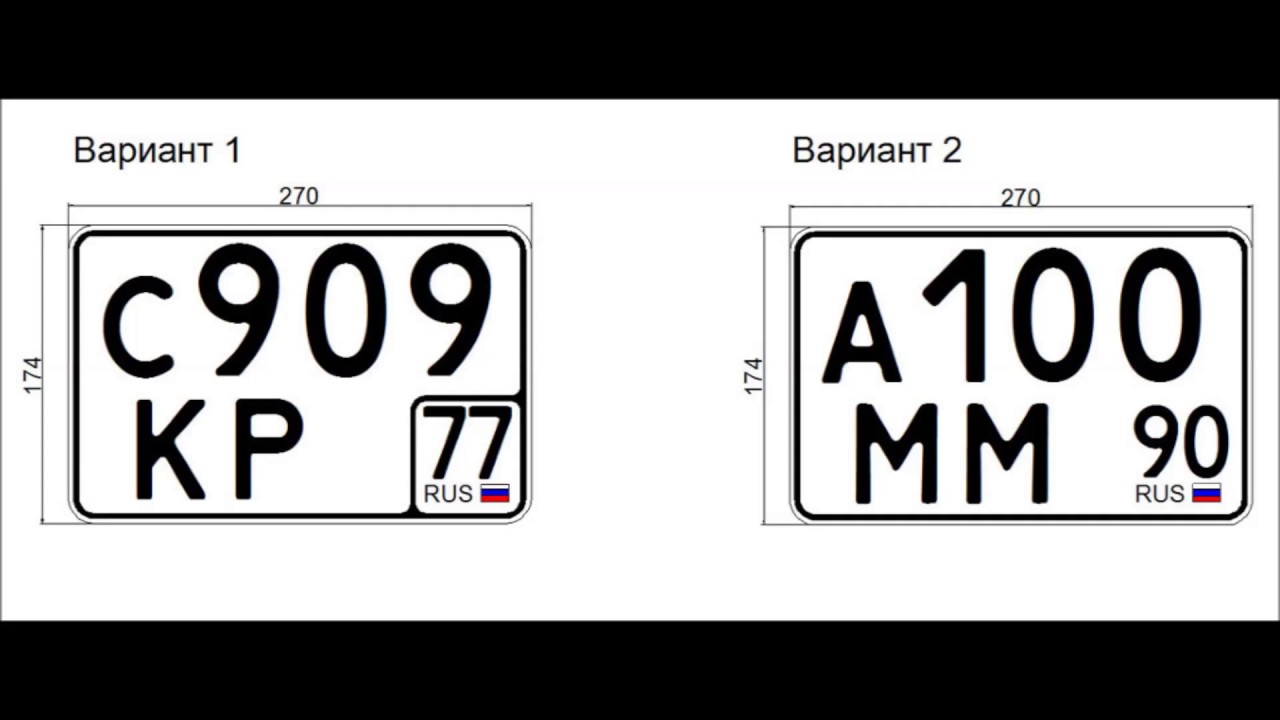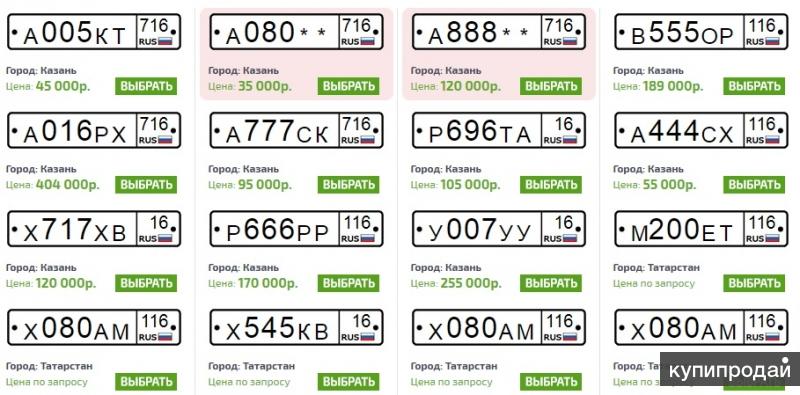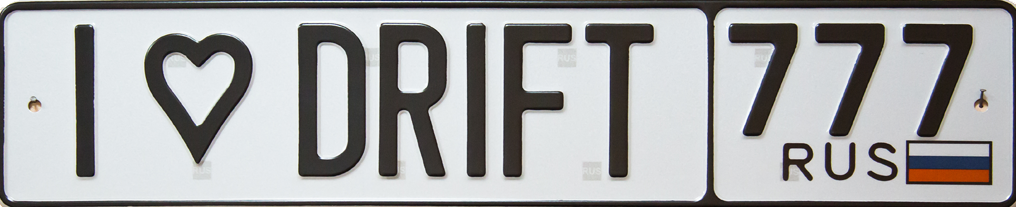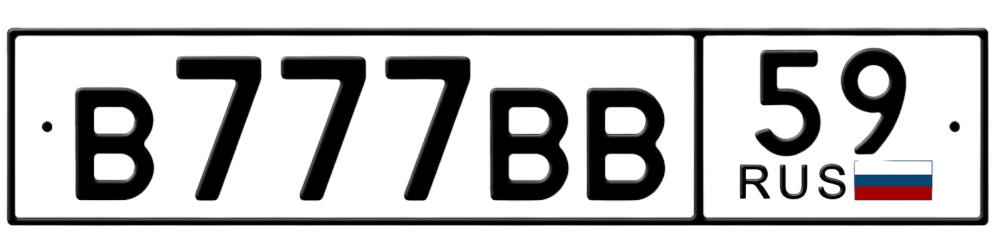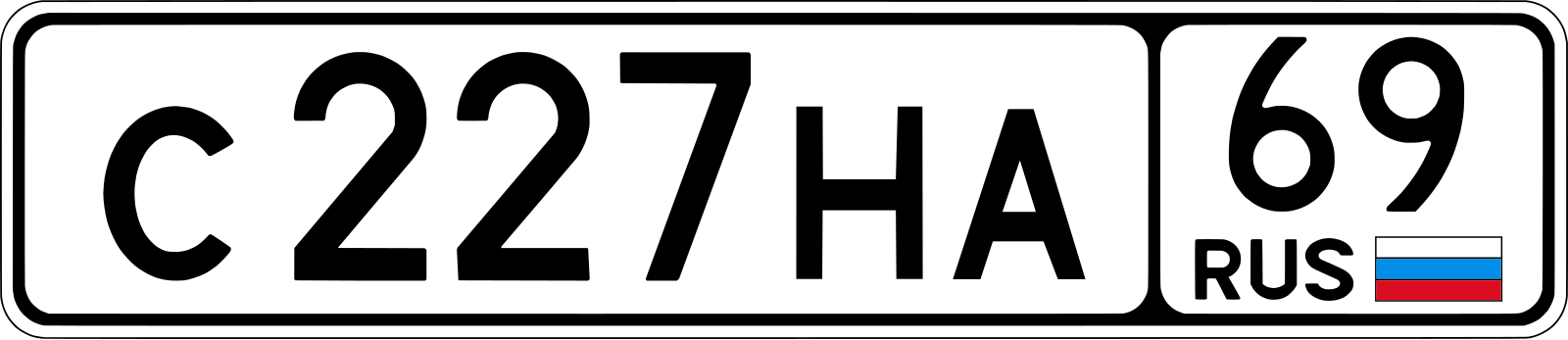
Шрифт для регистрационных номерных знаков (автомобильных номеров) / Хабр
Разработка комплексной автоматизированной системы, целью которой является автоматизация механизма контроля доступа на основании системы распознавания номерных знаков, сложная и, несомненно, комплексная задача. Для ее решения, в рамках квалификационной работы на степень бакалавра, мне потребовался не один месяц, и не одна сотня чашек чая.
Сегодня посмотрим на алгоритм и результаты решения локальной задачи по созданию шрифта в векторном формате согласно нормативной документации для отображения эталонов символов при корреляционном распознавании. На первом этапе углубимся в суть решаемой задачи.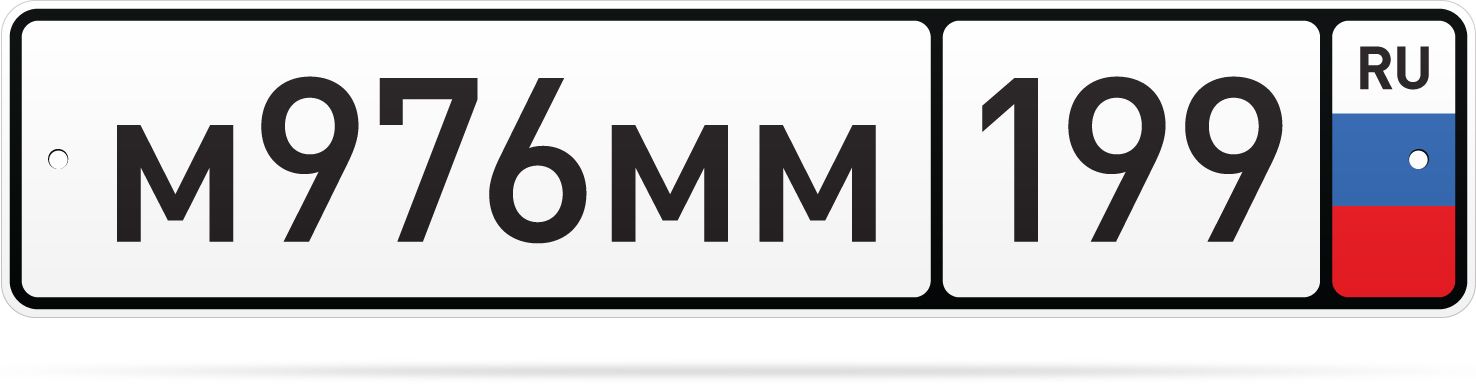
1 «Матчасть»: Регистрационный номерной знак Российской Федерации
Согласно ГОСТ Р 50577-93 «Знаки государственные регистрационные транспортных средств. Типы и основные размеры. Технические требования» большинство регистрационных знаков имеют вид, указанный на рисунке ниже.
Рис. 1.
Стандартные размеры регистрационного знака, которые составляют 520×112 мм. Символьные комбинации на стандартных номерных знаках определяются тремя буквами и тремя цифрами. Вышеприведенный ГОСТ Р 50577-93 ссылается на использование 12 букв кириллицы, которые имеют графические аналоги в латинском алфавите: А, В, Е, К, М, Н, О, Р, С, Т, У и Х. Надо заметить, что буквы по размеру шрифта меньше, чем цифры.
Начертание символов определяется шрифтом ЖР5 по ГОСТ 3489.2-71 «Шрифты типографские. Гарнитура Журнальная рубленая». На рисунке ниже приведена область из ГОСТа начертания шрифта для кеглей от 12 и выше.
Рис. 2.
Перед решением задачи, всегда необходимо провести исследование и определить «Решили ли уже эту задачу до меня?» и «Каким образом, ее решили?».
Следовательно, перейдем к следующему этапу, а именно поиску.
Поиск в интернете был недолгим, по правильному запросу «шрифт автомобильный номер», корпорация добра с радостью сообщила, что шрифт в векторе доступен для бесплатной скачки.
Нахождению «бесплатного сыра» радоваться сразу нельзя, поэтому необходим следующий этап — понять, насколько полученный шаблон позволит решить поставленную задачу.
3 «Анализ применимости»: RoadNumbers.otfБез тщательного анализа получить отличный результат, на мой взгляд, невозможно, поэтому рекомендуется потратить немного времени, чтобы потом судорожно не исправлять ошибки и недостатки.
И так, анализ показал следующее:
- В шрифте не хватает пары символов (в т.ч. символ «D», см. ниже)
- Шрифт заполнен в нижнем регистре
- Контуры только PostScript (у меня с ним возникали какие-то проблемы)
- Непонятные и лишние символы
Примечание: буква D используется в регистрационных знаках транспортных средств дипломатических представительств и торговых представительств иностранных компаний.
В результате была проведена работа по оптимизации шрифта, получившим атрибут «2.0»:
- В шрифте имеется все 12+1 символов
- Символы верхнего и нижнего регистра заполнены и обладают одинаковым начертанием (обеспечивает исключение ошибок)
- TrueType и PostScript версии
- Не используемые символы не имеют начертания (аналог «space»)
Рис. 3.
РезультатВ качестве результата представим шрифт, который пусть и не идеален, но позволяет решить глобальную задачу.
Имя шрифта: RoadNumbers